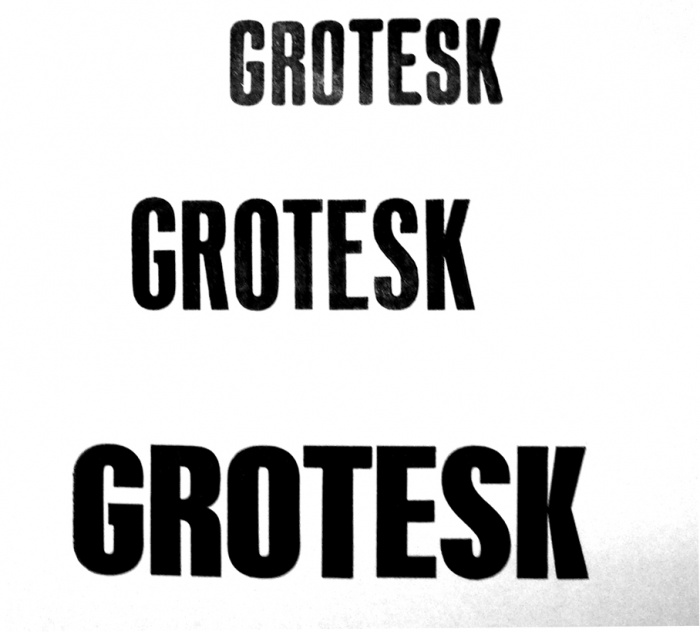
3 x Grotesk in Blei
Ich seh gar nichts mehr, wenn ich mir die drei Schhriften ansehe. Daher bitte ich noch einmal um eure Mithilfe für 3 mal Grotesk. Mein Ausbilder würde mich jetzt wieder mit diesem mitleidigen Blick strafen, aber ich komm nicht drauf.
die dritte und letzte Schrift ist die Placard Condensed. Die zweite und mittlere sollte eine Hanseatic sein, welche es digital von Bitstream als Swiss 924 in der großen 1000 Schriftensammlung, welche es auch in den diversen Corelprodukten gibt. Unter den Namen Hanseatic ist sie mir aber nie über den Weg gelaufen, sie steht so nur in diversen Alias-Listen drinnen.  Die erste Schrift hat was von der Eurostile Condensed Heavy, aber das R passt nicht und daher passe ich jetzt und mache Feierabend.
ja die dritte müsst edie Placard sein. Leider war meine Vorlage nicht so eindeutig, an der ich mich orientiert hatte. Hanseatic habe ich mir jetzt auch notiert.